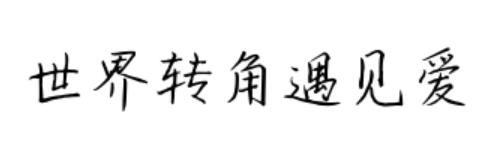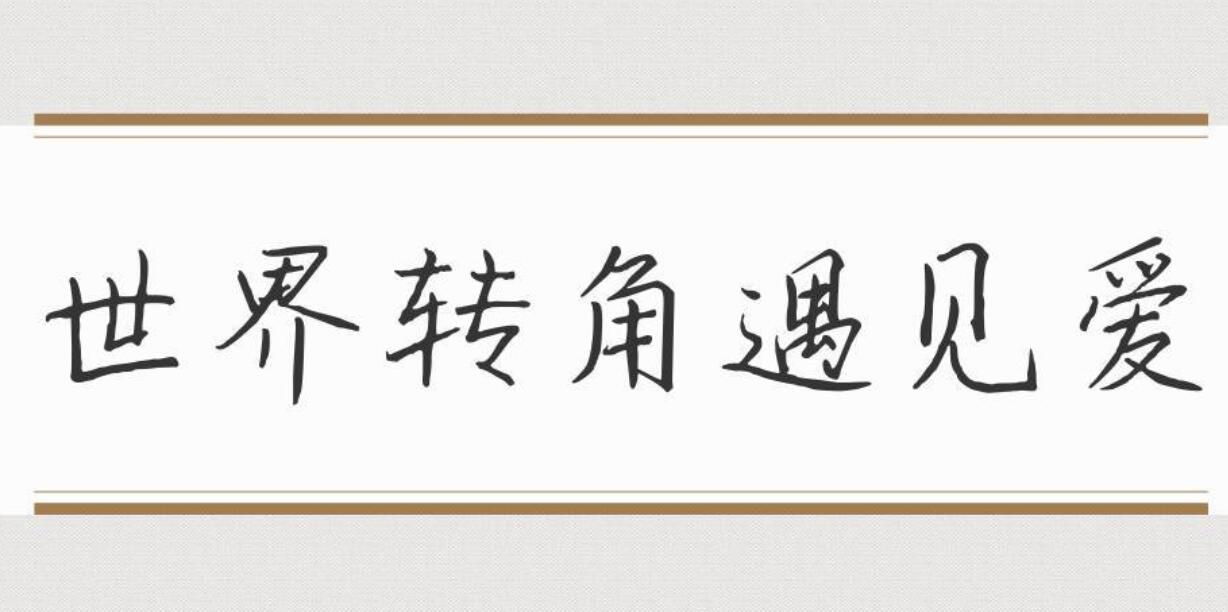
世界轉(zhuǎn)角遇見愛是文道字庫推出的一款非常不錯(cuò)的藝術(shù)字體,連貫字跡顯得干練而不凌亂,清新簡明,具有很好的視覺感,適合應(yīng)用于藝術(shù)設(shè)計(jì)、平面宣傳設(shè)計(jì)、網(wǎng)頁設(shè)計(jì),書法字帖等領(lǐng)域,歡迎喜歡冬日限定草莓字體的朋友前來下載使用。